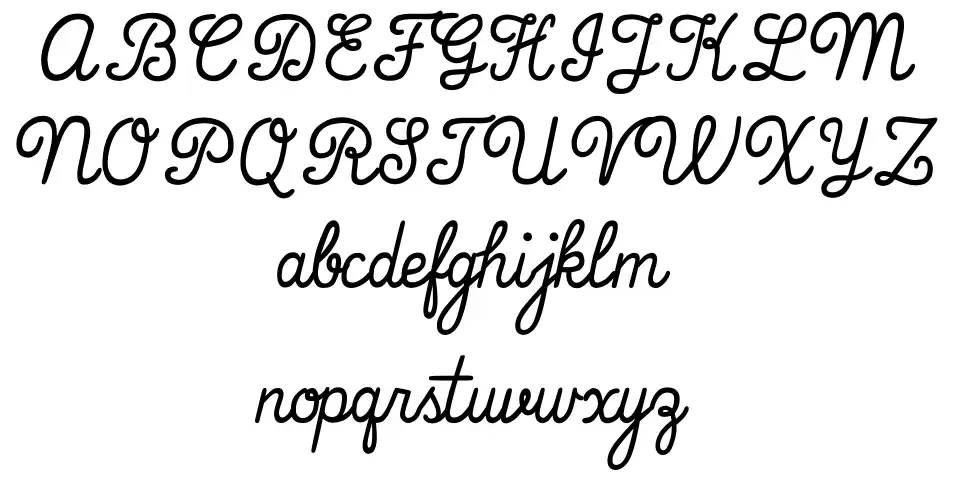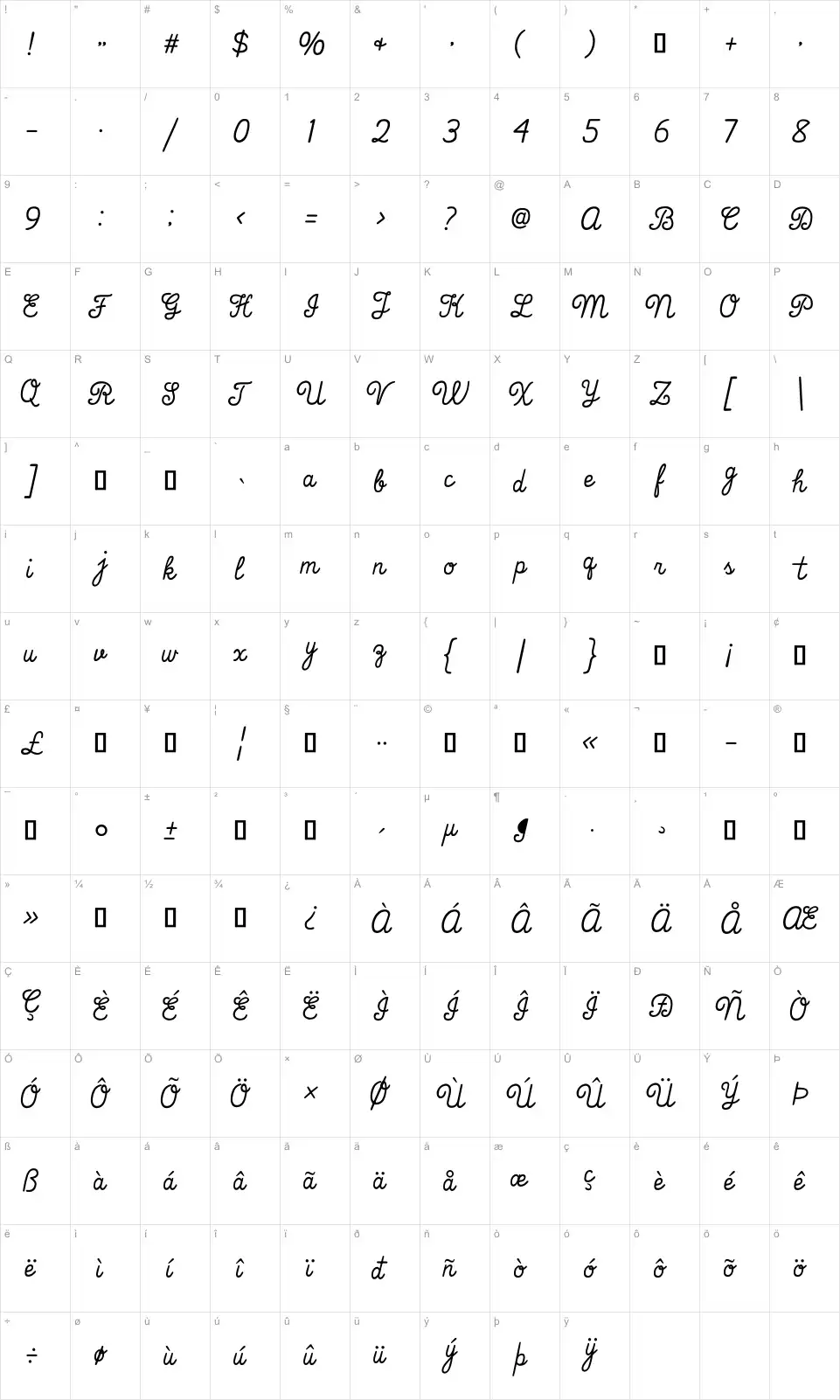
Descubra o que a fonte ‘That’s Font Folks!’ tem para oferecer, criada pelo designer GrandChaos9000. Esta fonte Script está disponível gratuitamente em formato TTF, tornando-a um recurso valioso para designers e criativos. Com a função de download ou geração de pré-visualização de texto personalizada online, você pode experimentar como a fonte se destaca em diferentes textos antes de utilizá-la. Com licença livre, um formato suave e uma categoria que abrange um amplo espectro de estilos, a font ‘That’s Font Folks!’ foi adicionada em 12 de julho de 2022. Atualmente, já foram baixados 2700 vezes, indicando sua popularidade e qualidade. Visite o site do designer para mais detalhes e recursos: http://grandchaos9000.deviantart.com.